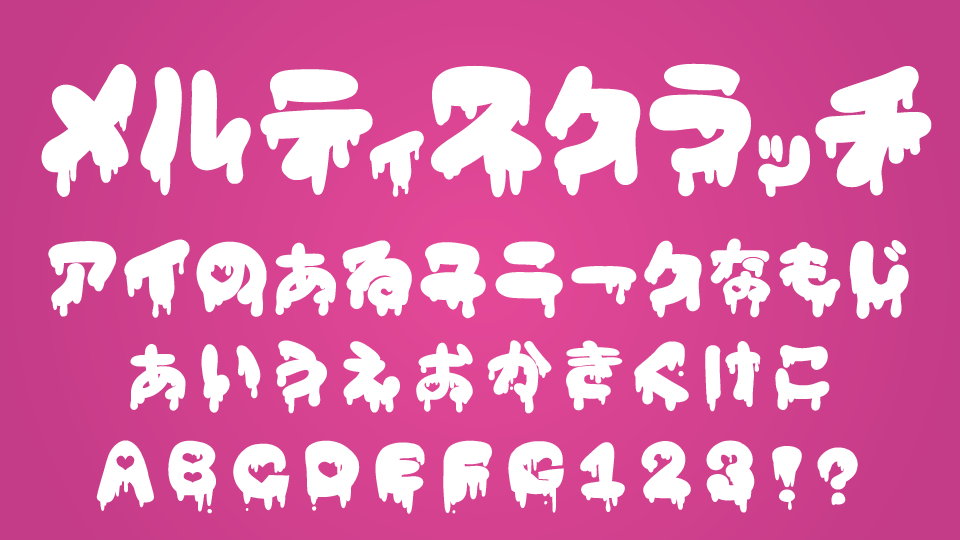
D.C.メルティスクラッチ
D.C.メルティスクラッチフォントは、溶け出すような遊び心のあるドリップ風のデザインフォントです。
丸みのあるシルエットがどこか愛嬌を感じさせ、手書きのような可愛らしい文字に、文字の輪郭から垂れ下がる液体がホラーっぽさ感じるギャップのあるユニークなデザインです。
ホラーやスプラッター系の世界観を演出するのにぴったなステキなフォントです。
D.C.メルティスクラッチ
収録文字は、極一部の漢字・ひらがな・カタカナ・アルファベット・数字・記号が収録されています。